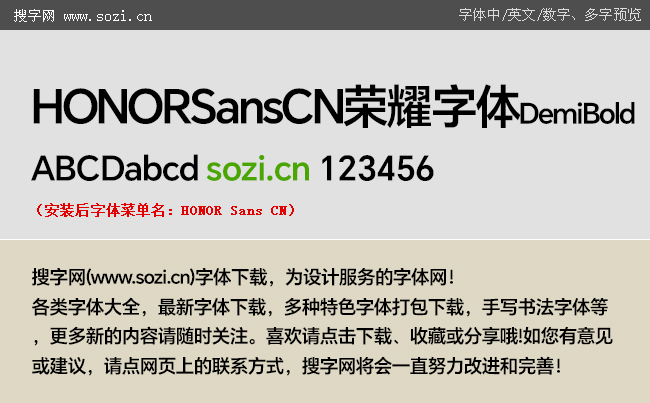
HONORSansCN荣耀字体DemiBold
搜字网给大家提供一款HONORSansCN荣耀字体DemiBold中文字体下载,荣耀字体由荣耀与方正字库携手打造,HONOR Sans荣耀字体是一款严谨稳健的黑体字体,该字体字形简洁生动,曲率平滑、线条优美,具有独特的人文风格和阅读关怀。适合书籍设计、网页设计、海报设计、包装设计等应用。